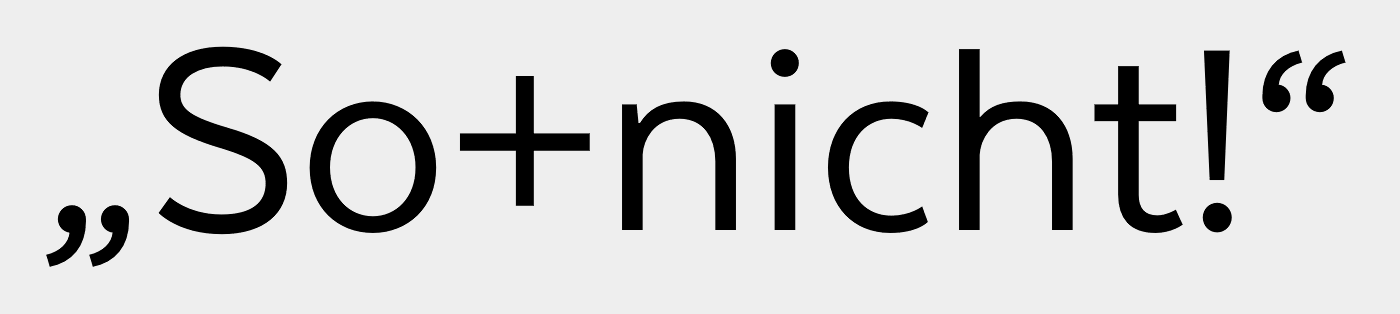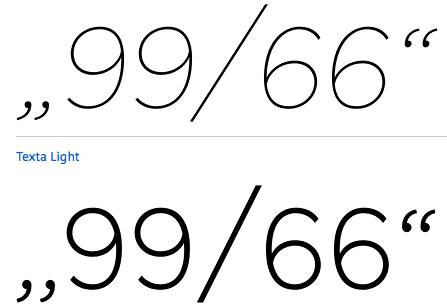
Schriftneuerwerbung Anführungszeichen-Problem
Möchte mir einen Schriftfont auf myfonts kaufen, nachdem ich mir die Glyphen, speziell das vordere "deutsche" Anführungszeichen angeschaut habe, bekomme ich Zweifel. Bei den meisten Fonts wirkt es zu weit.
Wird es nach eurer Erfahrung in dem dann gekauften Font genau so fehlerhaft sein?
Bei den meisten Fonts wirkt es zu weit
… und mir auf den ersten Blick auch irgendwie zu kippelig – fast als würden in den aufrechten Schnitten die Anführungszeichen aus der Kursiven verwendet.
Ja, so wie du es in den verschiedenen Myfonts-Vorschauen siehst, würde es – in dieser Version der Schrift – dann auch bei der Anwendung der gekauften Schrift aussehen. Aber bis zum 22. 11. (solange läuft das Angebot) ist ja noch etwas Zeit. Schreibe doch einfach dem Autor und bitte ihn, diese Fehler zu beheben!
Sehe ich jetzt auch, die Anführungszeichen wirken kursiv, in jedem Schnitt.
Der Distributor macht dann entsprechend Druck auf die Foundry, den Fehler im Font zu korrigieren.
So, wie Du, Ralf, es angedeutet hast, wird MyFonts dieses Anliegen an die Foundry weiterleiten. Ein Update wird nach deren Erfahrung ein paar Tage dauern.
Ja, das hatte ich mir vorgenommen. Bin selbst gespannt.
Hat sich bezüglich der Anführungszeichen eigentlich etwas ergeben? Das Angebot läuft ja nur noch bis morgen …
Nein Kathrin, leider nicht. Von myfonts war mir ja per Mail angekündigt, dass sie den Anbieter Latinotype informieren, ein Update dann gewöhnlich einige Tage dauern wird. Mein Nachhaken dort hatte nichts neues ergeben, mein Mail direkt an Latinotype war auch ohne Ergebnis.
Denke, Latinotype ist nicht bereit zu diesem Sonderpreis weiteren Aufwand zu betreiben. Mich überrascht aber, dass überhaupt eine Schriftfamile mit so gravierenden Fehler produziert wird, merkwürdigerweise ist der Lightfont ok.
Schade, dass die Latinotypes da nicht reagiert haben … Hmmm, ich habe gerade mal geschaut, diese hier funktionieren korrekt:
Wenn man die alternativen Anführungszeichen mag, dann könnte das also ein Ausweg sein.
Ich verstehe allerdigs überhaupt nicht, wie es überhaupt zu derart verbastelten Anführungszeichen kommenb kann. ist es doch eigentlich fast schwieriger das so zu bauen, als das in den doppelten anführungszeichen für alle möglichen Varianten gleich hin zu bekomen.
Das sind die Nebenwirkungen des heutigen Typedesigns. Es gibt immer mehr Zeichen und immer mehr Schnitte. Der Designer hilft sich dabei durch »Komponenten«, also setzt Buchstaben aus Instanzen von global änderbaren Einzelteilen zusammen, und er bearbeitet nur Master-Schnitte, nicht mehr jede Strichstärke selbst. In der Summe entstehen so abertausende Zeichen, die letztlich nie vom Designer selbst »angefasst« wurden, sondern sich nur dann korrekt ergeben, wenn alle Eingangsparameter perfekt waren. Kleine Unstimmigkeiten fallen so schwer auf – es sei denn man verbringt Wochen mit rigorosem Testen und prüfen jedes der tausenden entstandenen Einzelglyphen. Und da überrascht es auch nicht, dass gerade die Zeichen etwas stiefmütterlich behandelt werden, die in der eigenen Sprache gar nicht vorkommen.
Ja, das stimmt, und bei etlichen Schriften habe ich schon arg verunglückte Akzentbuchstaben gesehen. Allerdinmgs ist die Angelegenheit mit den Anführungsstrichen doch so einfach, dass ich mir hierfür längst ein Fontlab-Skript gebaut habe, dass eigentluich fast immer problemlos passt.
Aber jetzt eine Frage: Düfte man sich so einen Fehler auch notfalls selbst korrigieren?
Die meisten Nutzungsvereinbarungen sagen »nein«.
Unsere (bei FDI Type) erlauben das, aber ich würde trotzdem jedem davon abraten. Die heutigen Fontformate (OTF/TTF) sind einfach nicht darauf auslegt, in einem Fonteditor noch eimal editiert zu werden. Man wird meist eine Sache ändern und andere Sachen ungewollt kaputtmachen. Änderungen an Fonts sollten besser an den offenen Dateien gemacht werden.
Ich hatte das Angebot wahrgenommen und habe das Update bekommen.  :-)